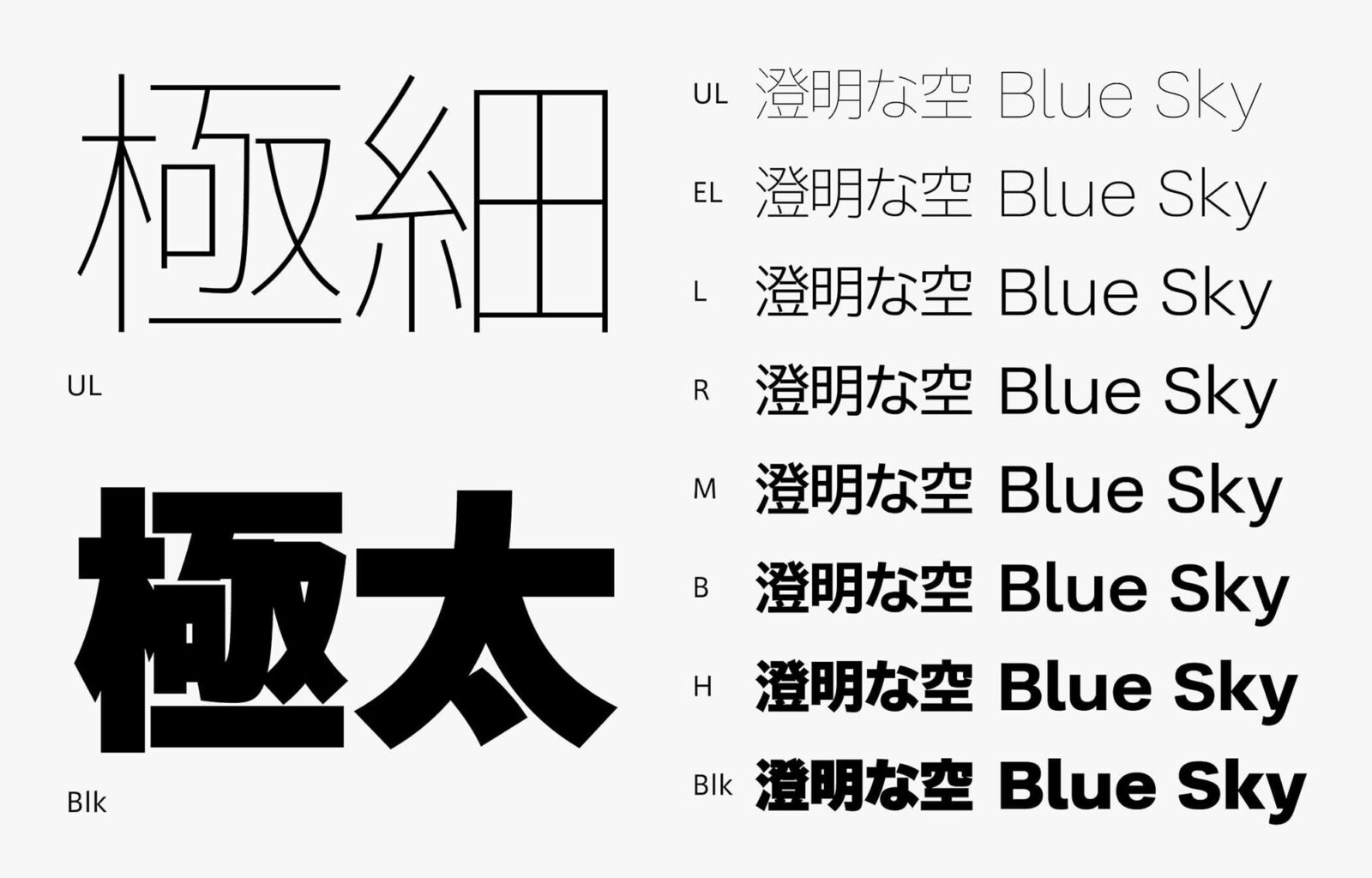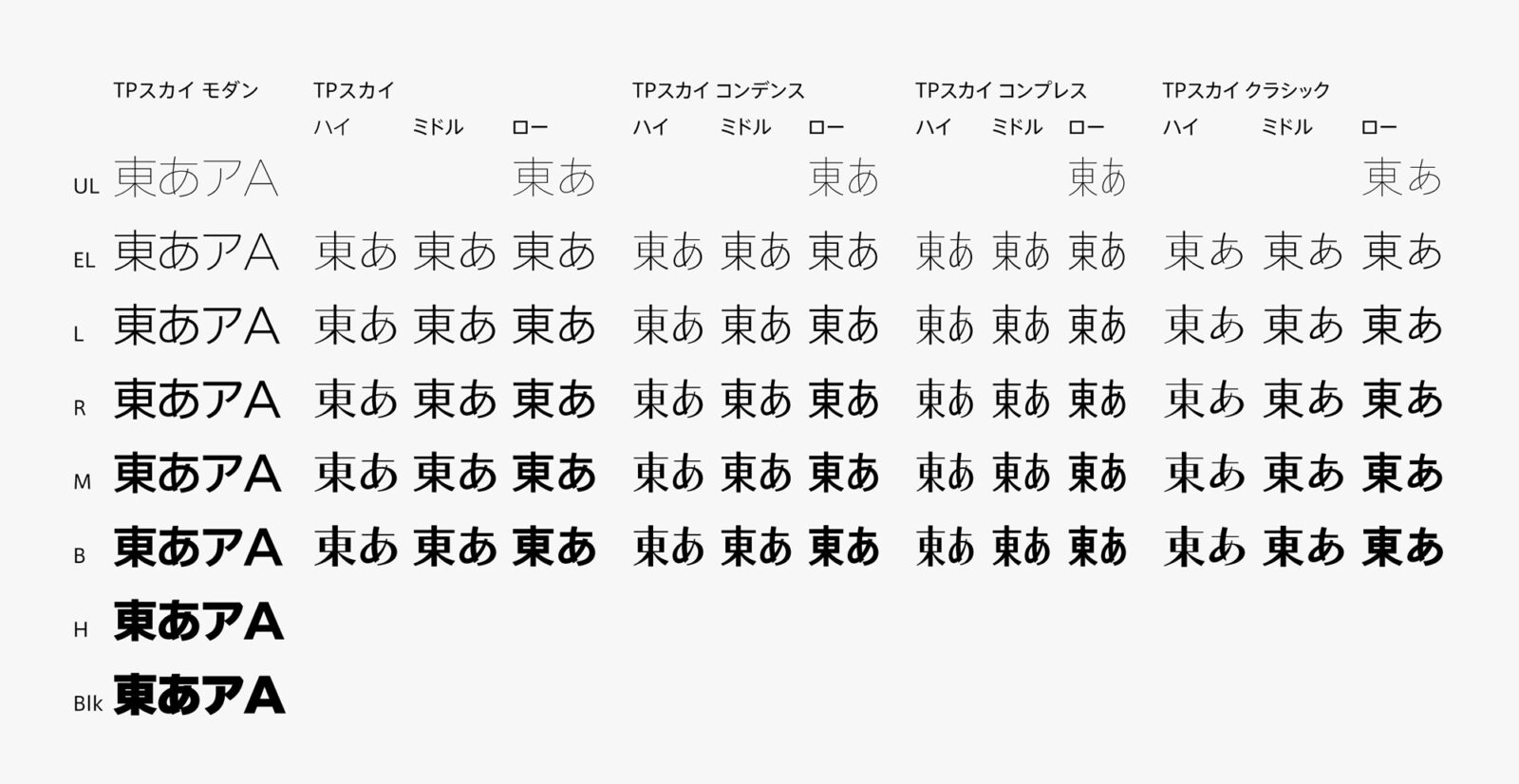
タイププロジェクト、「TPスカイ モダン」を8ウエイトに展開
TPスカイ シリーズの4種のローコントラストにも
繊細ウエイトのUL(ウルトラライト)を追加
タイププロジェクト株式会社(東京都練馬区 代表取締役社長 鈴木 功)は、「TPスカイ モダン」シリーズのBlk(ブラック)に加えてUL(ウルトラライト)からH(ヘヴィ)までの7ウエイトを追加したことを発表しました。これにより、「TPスカイ モダン」は8ウエイト展開となります。本日より、タイププロジェクトのサブスクリプションサービス「TPコネクト」での提供を開始いたします。
TPスカイ ファミリーは、ウエイト・コントラスト・字幅・フトコロ(字画内の内部空間)の4つの軸を持つ初めての日本語フォントです。その中でもTPスカイ モダンは、タイププロジェクトのフォントの中ではもっともフトコロが広く、安定感のある大らかな骨格のサンセリフ書体です。
TPスカイ モダンは、スペースいっぱいにデザインした大きな文字が特徴で、フトコロを広げるのと同時に字面も大きく設定し、仮名と漢字のサイズも近づけています。特太のウエイトであるTPスカイ モダンBlkは、画数に違いのある漢字・仮名・欧文を並べても整って見えるよう調整を重ねています。ULとEL(エクストラライト)は細身で軽やかさや透明感が強みのウエイトで、ほぼ同じに設定した線幅により均一感を出すことができます。L(ライト)からH(ヘヴィ)の線幅は視覚的に揃って見えるよう設計しているので、黒みが安定した組版を実現します。
欧文は、和文と同じく大きなフトコロと大らかな骨格を持たせることにより、力強い印象を与える落ち着いたオーソドックスなデザインです。ウエイトごとに高さを調整しているため、見え方のバランスがよく、組んだ際の自然な見え方を実現しています。
タイププロジェクトの代表取締役 鈴木 功は、「TPスカイ モダンは、明るく親しみやすいという印象と、ベタ組みとの相性が良くつぶれにくいという機能を持ち合わせた書体です。TPスカイファミリーの中でも、透き通った大きな声で語るような若さあふれる元気の良い書体を目指しました。極細から極太まで幅広くウエイトを展開しているので、細いウエイトでは空間を広く取った軽やかさ、太いウエイトではインパクトのある力強さと表現したい内容に合わせてお選びいただけると思います」と述べています。
TPスカイ モダンは、UL(ウルトラライト)、EL(エクストラライト)、L(ライト)、R(レギュラー)、M(ミディアム)、B(ボールド)、H(ヘヴィ)、Blk(ブラック)の全8ウエイトです。
TPスカイ モダンのウエイト展開に合わせて、新たにTPスカイ ローコントラストと、TPスカイ コンデンスおよびコンプレスのローコントラスト、TPスカイ クラシック ローコントラストにも繊細なUL(ウルトラライト)を追加しました。これにより、TPスカイ ファミリーは、TPスカイ モダン 8ウエイト、TPスカイ48フォント(ウエイト×コントラスト×字幅)、TPスカイクラシック(ウエイト×コントラスト)16フォントの全72フォントになりました。